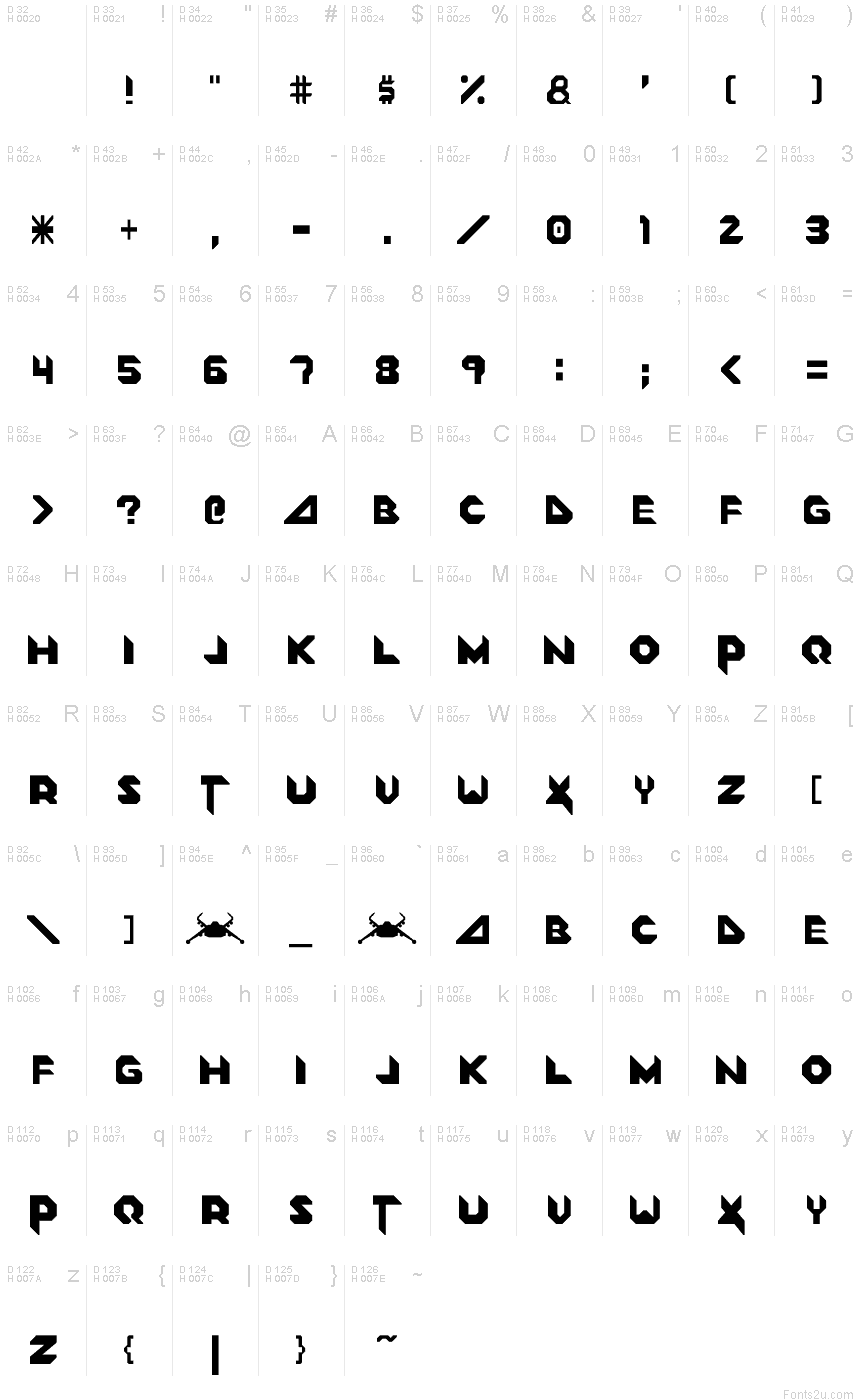
Descent ][ Bold è un font display techno gratuito caratterizzato da una geometria tagliente e un mood quasi industriale. Le forme squadrate, le diagonali nette e i contrografismi ritagliati conferiscono a ogni parola un senso di movimento in avanti, come un'incisione sul fianco di una macchina futuristica. Abbina questo font a un sans serif semplice e leggero per i corpi più piccoli, così da mantenere la leggibilità e lasciare che il logo o il titolo mantengano il loro impatto.
Con Descent ][ Bold puoi creare grafiche di forte impatto per titoli di videogiochi, poster sci-fi, titoli di coda, branding per e-sport, flyer tecnologici e packaging sperimentale. La densità delle forme nere e il ritmo angolare rendono bene nelle grandi dimensioni, dove ogni intaglio e smusso diventa parte della composizione grafica. Questo font gratuito brilla quando tratti il testo come un logo, mantenendo brevi i testi e audace e arioso il layout.